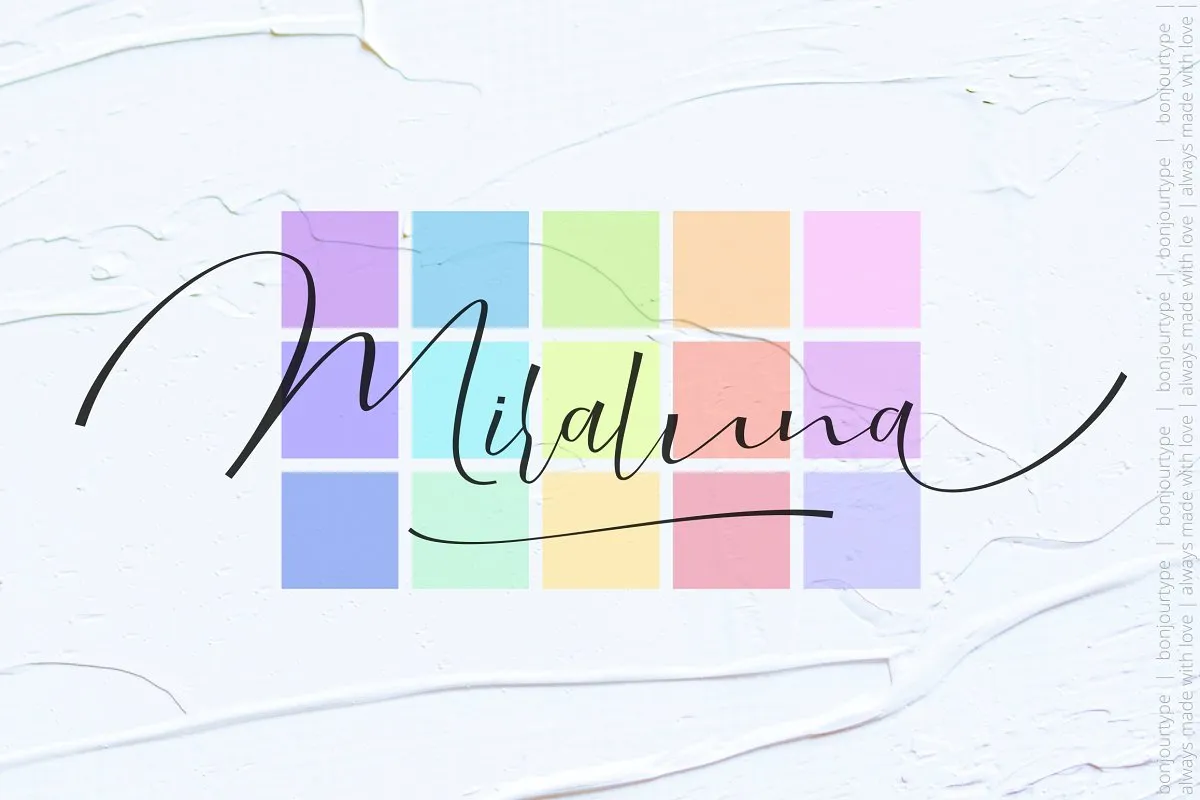
Miraluna é uma elegante fonte script criada para quem busca uma opção moderna e sofisticada para seus projetos digitais ou impressos. Esta fonte foi feita a mão, fornecendo um acabamento suave e perfeito para criar textos personalizados e estilizados. Com Miraluna, você pode incorporar o texto em logotipos, embalagens de produtos ou até mesmo materiais de merchandising. Este conjunto completo de letras maiúsculas e minúsculas, símbolos multilingue, números e pontuação torna a fonte perfeita para diferentes técnicas de impressão e artesanato como costura, corte com laser ou aplicação de papel dourado. Com seu texto cortado na forma, Miraluna oferece qualidade superior que mantém o texto coerente. Este é um ativo valioso para designers gráficos e criadores de produtos, proporcionando uma fonte única capaz de transformar qualquer projeto em algo extraordinário. Com sua textura cortada, Miraluna será ideal para qualquer projeto impresso ou digital, garantindo o melhor resultado sempre.